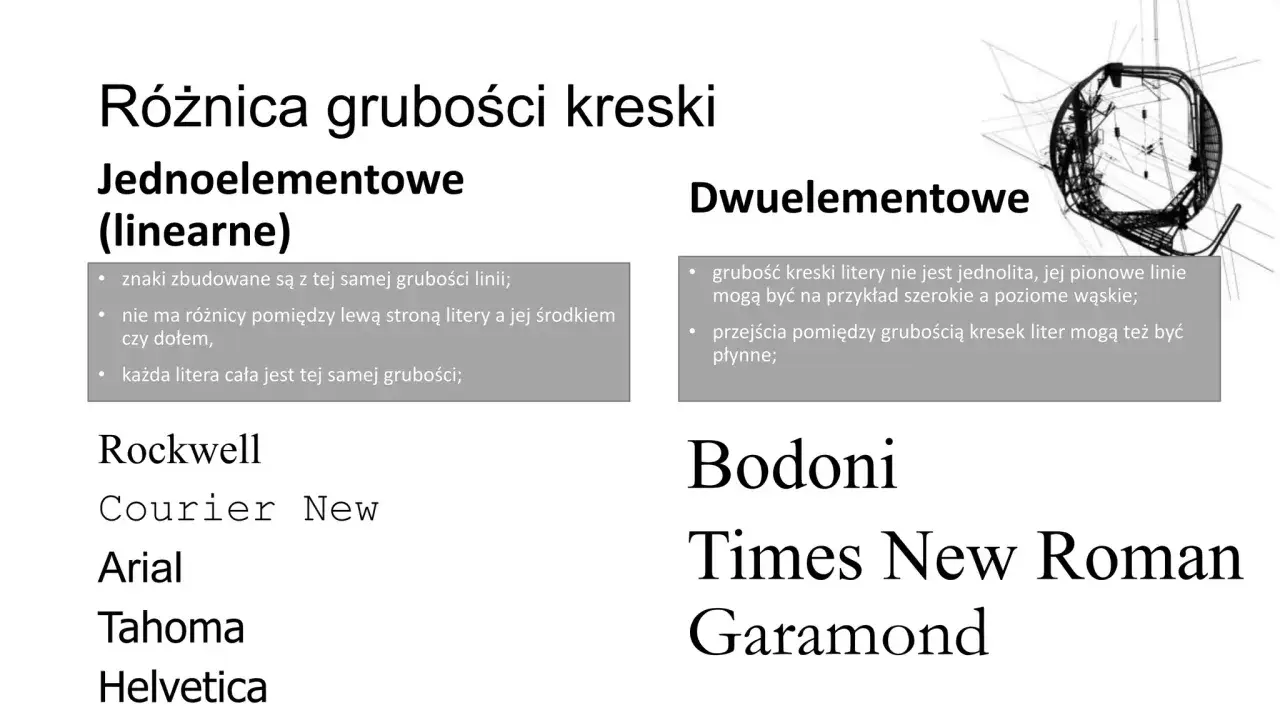
Czcionka dwuelementowa bezszeryfowa nie jest po prostu kolejnym sansem z katalogu fontów. To krój, w którym brak szeryfów łączy się z wyraźnym kontrastem między cienkimi i grubymi liniami, a to daje zupełnie inny charakter niż w zwykłych, równych groteskach. W tym tekście pokazuję, jak taki zapis rozpoznać, gdzie działa najlepiej i kiedy lepiej postawić na spokojniejszą alternatywę.
Najkrótsza odpowiedź brzmi tak
- To bezszeryfowy krój o wyraźnym kontraście kreski, a nie „zwykły” neutralny sans.
- Najłatwiej rozpoznasz go po braku szeryfów i różnicy między cienkimi a grubymi fragmentami liter.
- Najlepiej sprawdza się w nagłówkach, logo, plakatach i materiałach marki, które mają budować klimat.
- Do długich bloków tekstu i bardzo małych rozmiarów bywa mniej bezpieczny niż prostszy, bardziej równomierny krój.
- Przy wyborze warto testować go na telefonie, w druku i w różnych wagach, bo efekt szybko zmienia się ze skalą.
Co właściwie oznacza ten opis kroju
W typografii taka klasyfikacja łączy dwie cechy: bezszeryfowość i dwuelementowość, czyli wyraźny kontrast między cienkimi i grubymi częściami liter. To ważne, bo wiele osób automatycznie zakłada, że każdy bezszeryfowy font wygląda podobnie, a w praktyce różnice potrafią być bardzo duże. Jeden krój jest neutralny i techniczny, inny bardziej elegancki, a jeszcze inny wyraźnie pokazuje rękę projektanta.
Ja patrzę na to tak: ten opis nie mówi wyłącznie o braku ozdobników, ale o charakterze konstrukcji. Litery nadal są proste w odbiorze, jednak ich rytm nie jest jednorodny. Dzięki temu krój może wyglądać bardziej redakcyjnie, luksusowo albo po prostu bardziej „projektowo” niż standardowy sans używany w interfejsach.
| Cecha | Neutralny bezszeryfowy | Dwuelementowy bezszeryfowy | Szeryfowy dwuelementowy |
|---|---|---|---|
| Szeryfy | Brak | Brak | Są obecne |
| Kontrast grubości | Niski lub umiarkowany | Wyraźny |
| Odbiór | Neutralny, techniczny | Elegancki, bardziej ekspresyjny | Klasyczny, editorialowy |
| Najczęstsze użycie | UI, długi tekst na ekranie | Nagłówki, branding, plakaty | Tekst ciągły, druk, publikacje |
W materiałach ZPE taki krój pokazano na przykładzie Britannic, opisywanego jako bezszeryfowy dwuelementowy font o pionowej osi i wysokim kontraście kreski. Z kolei w Typotece Aligant został opisany jako bezszeryfowy dwuelementowy krój o dużym skontrastowaniu cienkich i grubych elementów. To dobre przykłady, bo pokazują, że bezszeryfowość nie musi oznaczać płaskiego, jednorodnego wyglądu. Kiedy już to rozumiesz, łatwiej przejść do rozpoznawania takiego kroju w praktyce.
Kolejna rzecz, którą warto doprecyzować: dwuelementowość nie oznacza tutaj, że litera ma „dwie części” w sensie konstrukcji a albo g. Chodzi przede wszystkim o różnicę w grubości linii. To częste źródło pomyłek, zwłaszcza w zadaniach szkolnych i egzaminacyjnych, gdzie trzeba szybko rozpoznać krój po jednym kadrze.
Jak rozpoznać taki krój na pierwszy rzut oka
Najprościej zacząć od trzech obserwacji. Po pierwsze, sprawdź, czy litery nie mają szeryfów. Po drugie, porównaj grubość pionów i poziomów. Po trzecie, zwróć uwagę na to, czy cienkie elementy nie wyglądają na przypadkowe, tylko tworzą spójny rytm całego alfabetu. Jeśli te trzy warunki występują razem, bardzo możliwe, że patrzysz właśnie na taki bezszeryfowy, kontrastowy krój.
- Patrz na kilka liter naraz - najlepiej na „a”, „e”, „n”, „o” i „g”, a nie tylko na jeden znak.
- Porównaj piony i poprzeczki - w mocniej zróżnicowanych krojach różnica grubości jest widoczna od razu.
- Sprawdź oś liter okrągłych - w bardziej klasycznych przykładach bywa pionowa, co wzmacnia elegancki charakter.
- Przetestuj mały rozmiar - jeśli cienkie fragmenty znikają, krój może być zbyt delikatny do drobnego składu.
- Nie myl kontrastu z ozdobnością - brak szeryfów nie znaczy jeszcze prostoty, a obecność kontrastu nie oznacza szeryfowego kroju.
W praktyce takie kroje bywają mylone z nowoczesnymi groteskami albo z fontami, które mają tylko „lekko narysowany” charakter. To dlatego lubię sprawdzać je w powiększeniu i w realnym kontekście, a nie na pojedynczym podglądzie. Jeden znak może oszukać, cały wyraz zwykle już nie.
Jeśli krój ma duży kontrast, ale nadal nie ma szeryfów, to sygnał, że projektant celował raczej w wyrazistość niż w neutralność. I właśnie ta cecha odróżnia go od wielu popularnych sansów używanych masowo w aplikacjach i systemach identyfikacji wizualnej. To prowadzi do najważniejszego pytania: gdzie taki styl naprawdę pracuje na projekt, a gdzie tylko przeszkadza.
Gdzie taki styl działa najlepiej w projektach reklamowych
Najczęściej wygrywa tam, gdzie tekst ma budować klimat, a nie tylko przekazywać informację. W reklamie i identyfikacji wizualnej to spora różnica, bo krój może od razu ustawić ton marki: bardziej premium, bardziej editorialowy, czasem nawet bardziej artystyczny. Zwykły sans bywa bezpieczniejszy, ale też łatwiej znika w tle.
| Zastosowanie | Dlaczego działa | Kiedy uważać |
|---|---|---|
| Logo typograficzne | Zapada w pamięć i nadaje znakowi charakter | Przy małej skali cienkie fragmenty mogą się gubić |
| Nagłówki landing page | Buduje hierarchię i mocny pierwszy akcent | Nie przesadzać z wielkością przy bardzo ciasnym layoucie |
| Plakaty i okładki | Dobrze pracuje z dużą przestrzenią i kontrastem | Wymaga świadomego światła i wyraźnego tła |
| Pakowanie i etykiety | Dodaje jakości, nowoczesności i precyzji | Na małej powierzchni trzeba pilnować czytelności |
| Długi tekst | Może wyglądać szlachetnie w publikacji editorialowej | W małym stopniu pisma bywa zbyt delikatny dla komfortu czytania |
W materiałach brandingowych lubię ten efekt szczególnie wtedy, gdy marka chce wyglądać nowocześnie, ale nie zimno. To nie jest krój do wszystkiego, jednak w odpowiednim kontekście robi dokładnie to, czego oczekuje projektant: podnosi jakość odbioru bez nadmiaru ozdobników. Jeśli jednak potrzebujesz podobnego wrażenia, ale mniejszego ryzyka, trzeba go dobrać z głową, nie tylko po wyglądzie miniatury.
Jak dobrać podobny krój, żeby projekt nie stracił czytelności
Jeśli szukasz fontu o podobnym charakterze, zacznij od celu, a nie od estetyki. Najpierw odpowiedz sobie na trzy pytania: gdzie tekst będzie używany, jak duży ma być i czy ma pracować jako główny akcent, czy tylko jako element wspierający. Dopiero potem porównuj konkretne rodziny krojów.
- Określ nośnik. Inny font wybiorę do logotypu, inny do interfejsu, a jeszcze inny do plakatu.
- Sprawdź zakres wag. W wielu rodzinach najlepiej sprawdza się regular, medium i semibold, a cienkie odmiany zostawiam do dużych formatów.
- Testuj skalę. Ustaw ten sam napis w rozmiarach 14 px, 24 px i 48 px, a potem obejrzyj go także w druku.
- Porównaj dwa tła. Ciemne i jasne tło często ujawniają słabości cienkich kresek szybciej niż sam podgląd w edytorze.
- Dodaj font pomocniczy. Do dłuższych akapitów często lepiej dobrać spokojniejszy, bardziej neutralny sans.
W 2026 szczególnie praktyczne są rodziny variable, bo pozwalają dopasować grubość i czasem też szerokość bez zmiany całej stylistyki projektu. To przydatne, jeśli chcesz utrzymać jeden charakter w kilku kanałach naraz: na stronie, w social mediach i w druku. Ja traktuję to jako sposób na kontrolowanie efektu, a nie jako sztuczkę dla samej technologii.
Warto też pamiętać, że sam kontrast nie wystarczy. Liczy się odstęp między literami, interlinia, szerokość kolumny i jakość renderowania. Jeśli cienkie elementy zaczynają się rozpadać, krój nie jest „zły” sam w sobie, tylko źle dobrany do środowiska, w którym pracuje.
Kiedy ten wybór wzmacnia markę, a kiedy lepiej go odpuścić
Największą siłą takiego kroju jest to, że potrafi wyglądać jednocześnie nowocześnie i wyraziście. To świetna wiadomość dla marek z obszaru designu, mody, kultury, beauty, premium i części projektów technologicznych, które nie chcą brzmieć zbyt chłodno. Jeśli komunikat ma być elegancki, ale nie akademicki, taki krój potrafi zrobić więcej niż cała warstwa dekoracji.
Są jednak sytuacje, w których ten sam wybór osłabia projekt. Gdy masz mało miejsca, niski kontrast druku albo konieczność długiego czytania na małym ekranie, lepiej postawić na prostszy i bardziej stabilny sans. Zbyt delikatne cienkie linie potrafią wyglądać efektownie na mockupie, a potem znikają w realnym użyciu. To klasyczny błąd: projekt wygląda dobrze w prezentacji, ale traci w użytkowaniu.
Jeśli miałbym zostawić jedną praktyczną zasadę, brzmiałaby tak: im bardziej ekspresyjny bezszeryfowy krój, tym dokładniej trzeba pilnować skali, światła i kontekstu. Taki font nie powinien być dekoracją oderwaną od treści, tylko narzędziem, które wzmacnia komunikat. Właśnie dlatego najlepiej działa wtedy, gdy jest świadomie wybrany, a nie wyłoniony przypadkiem z pierwszej strony katalogu.